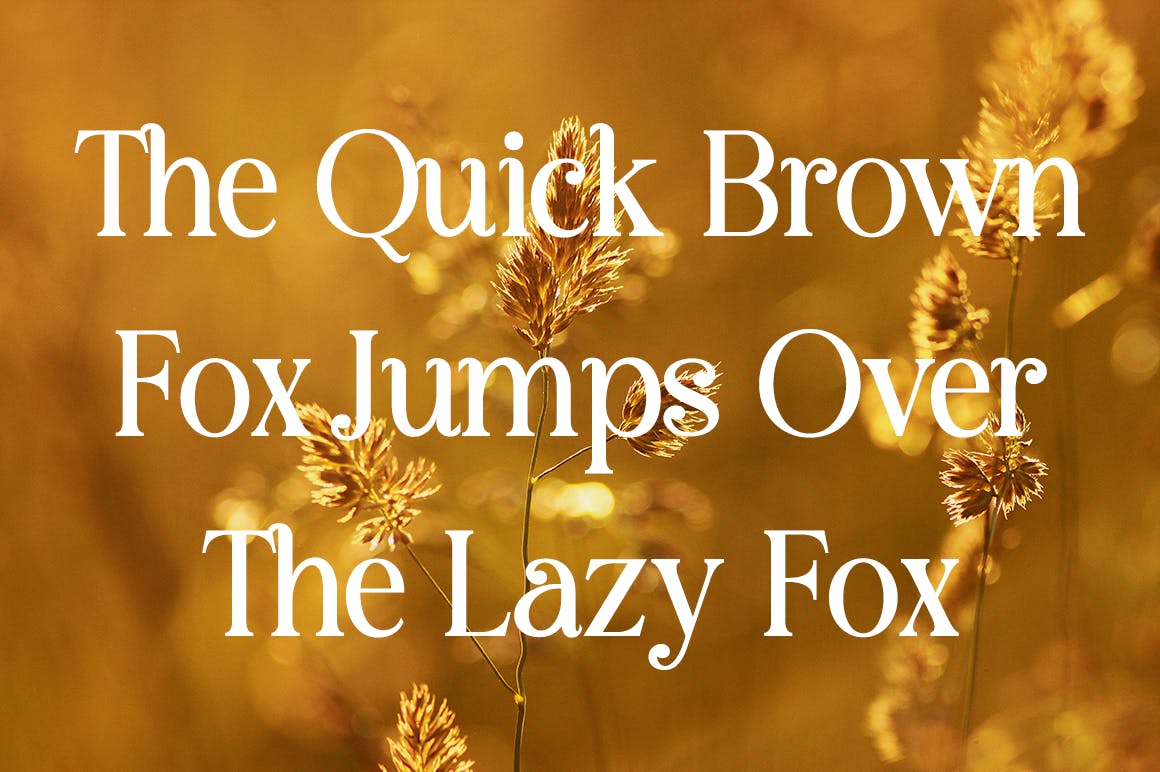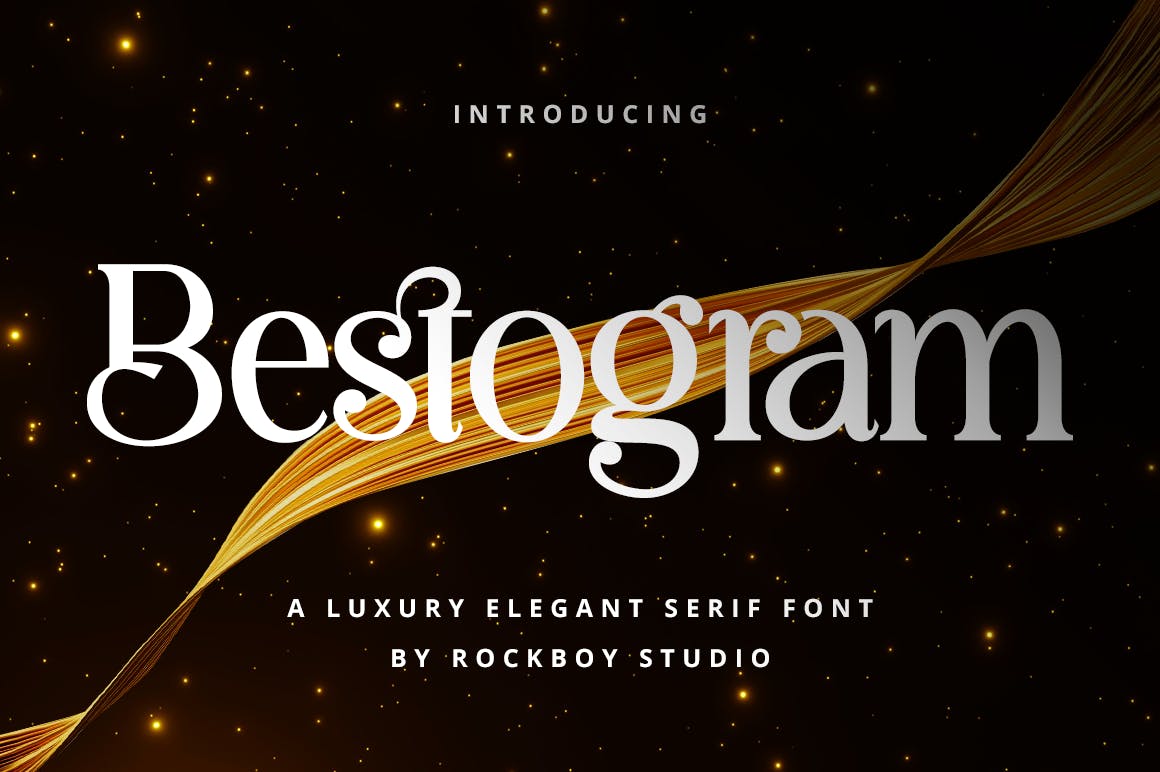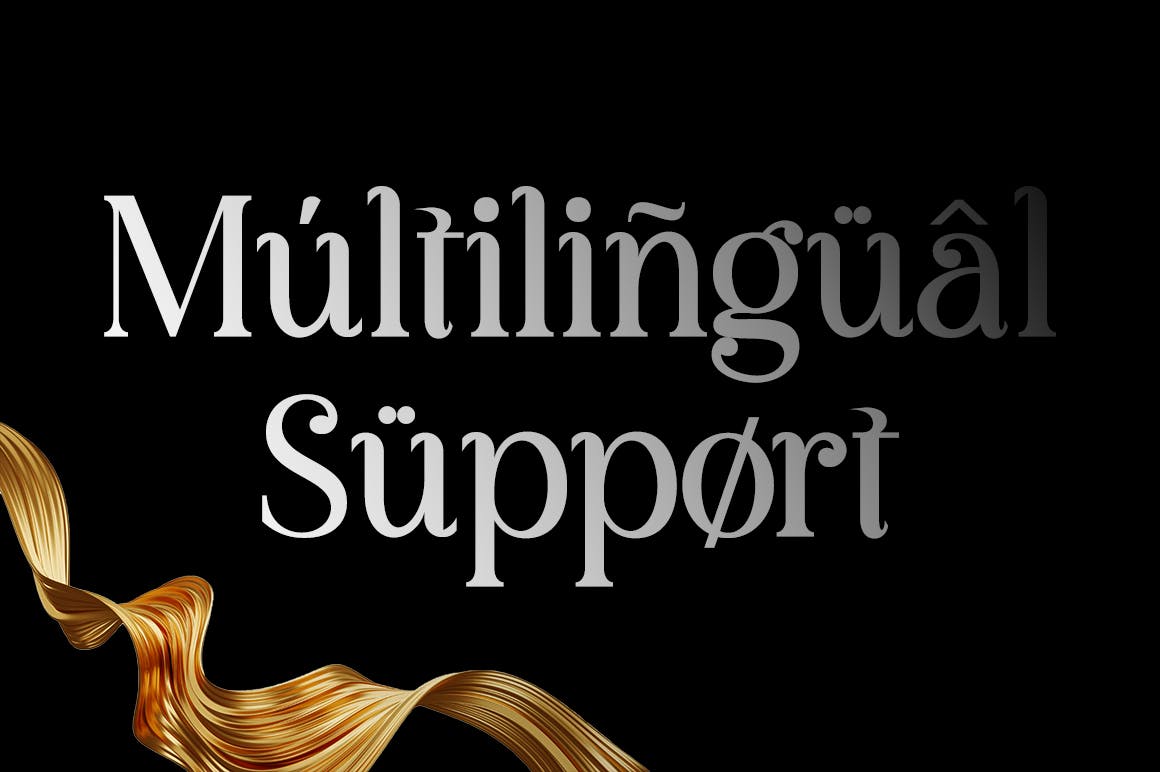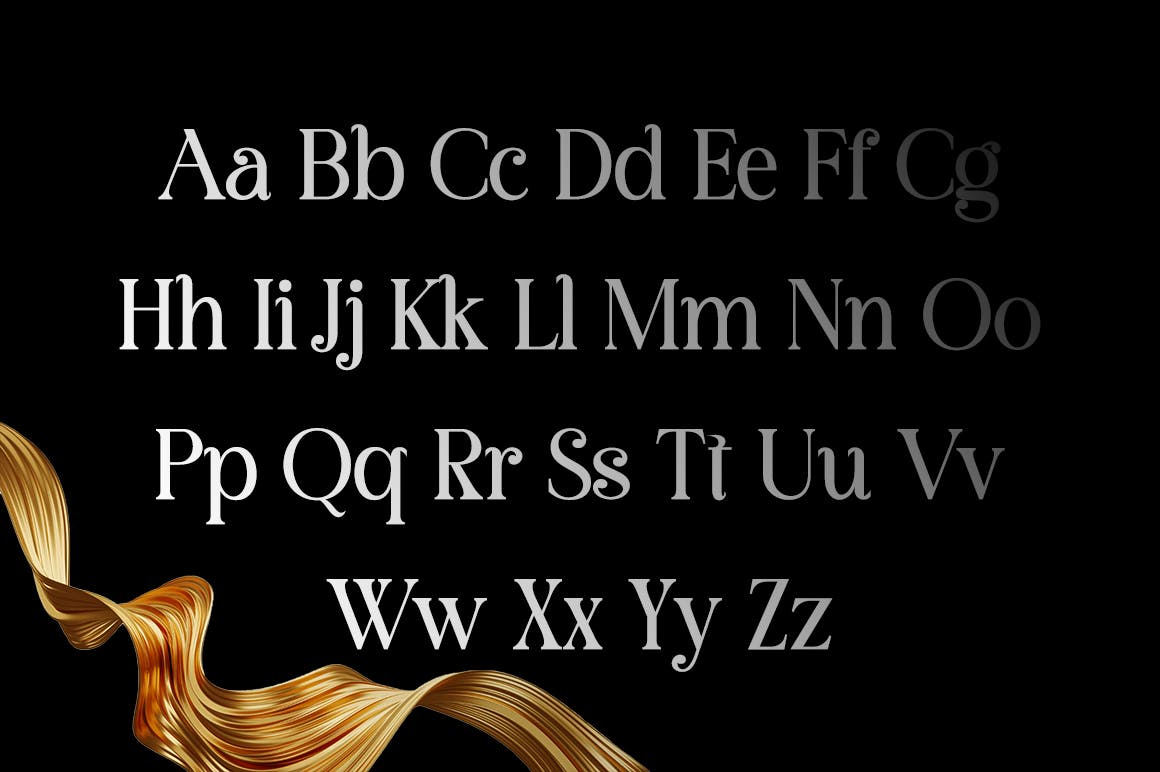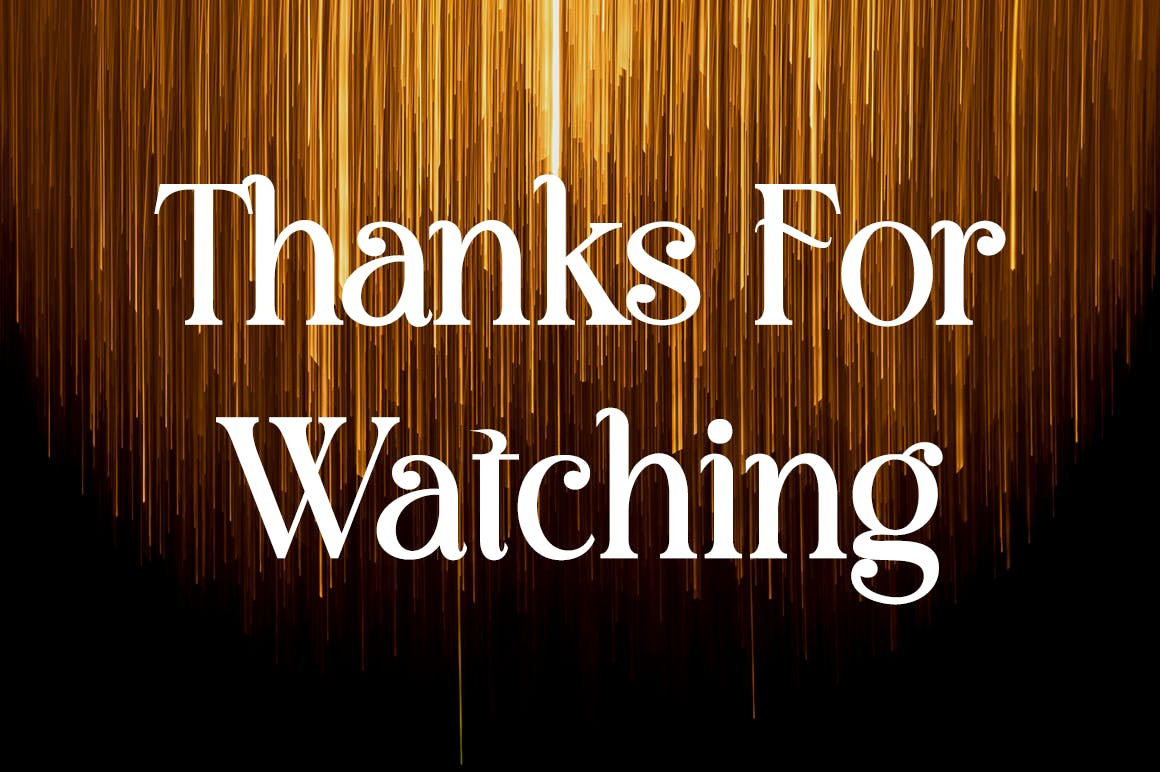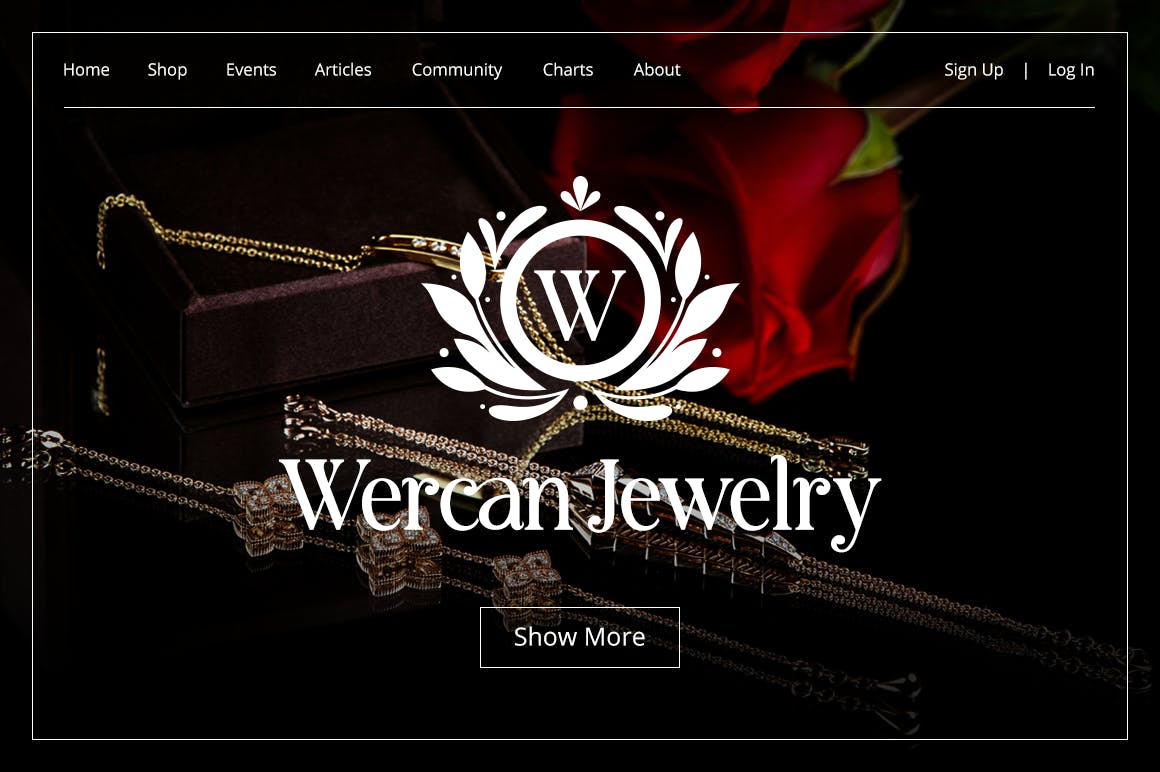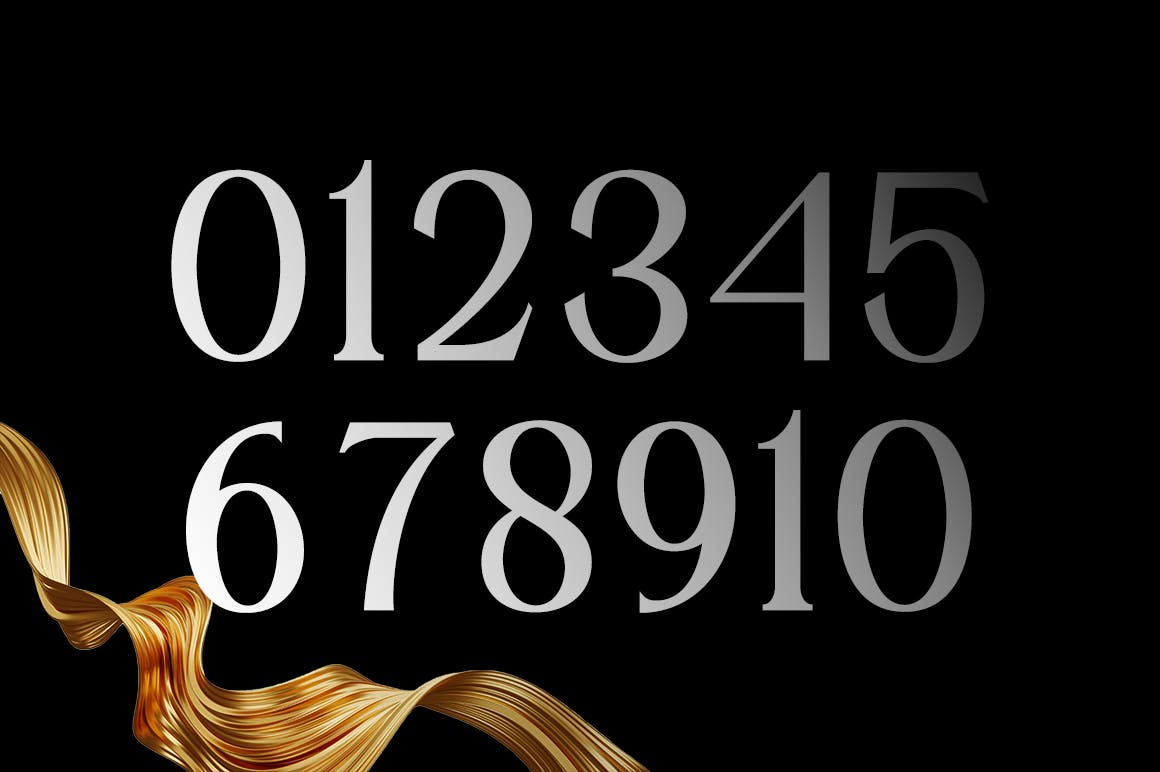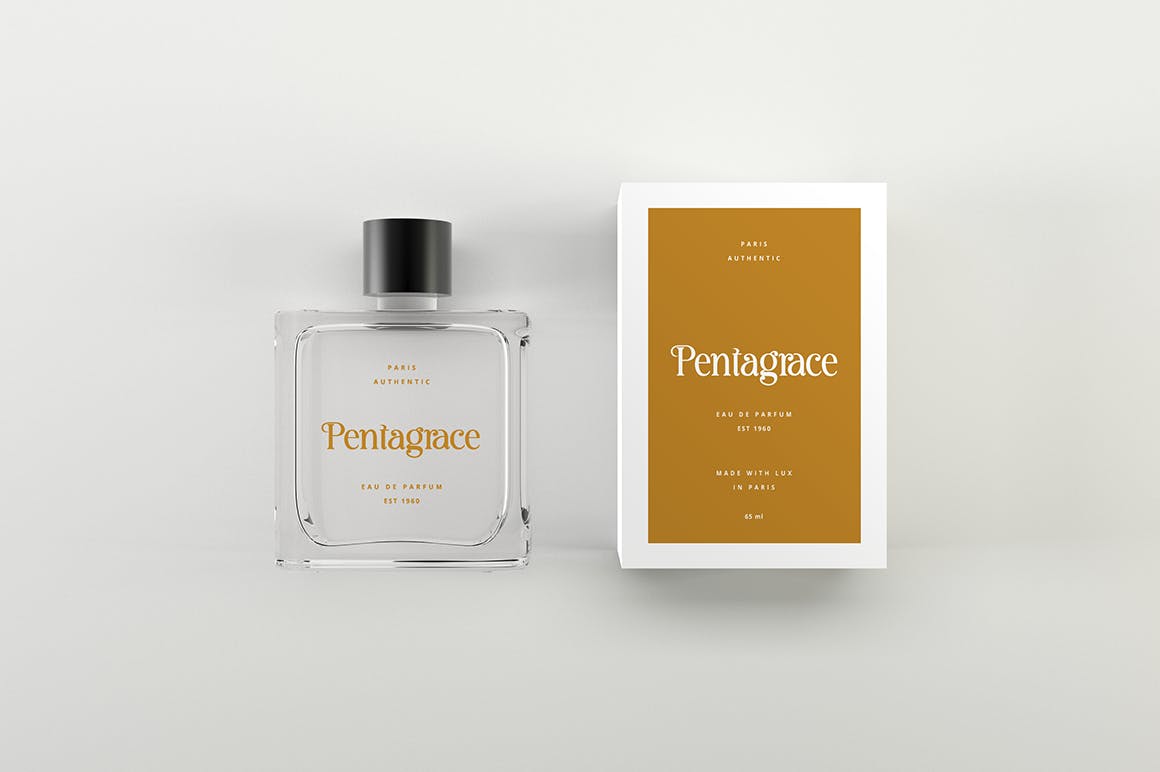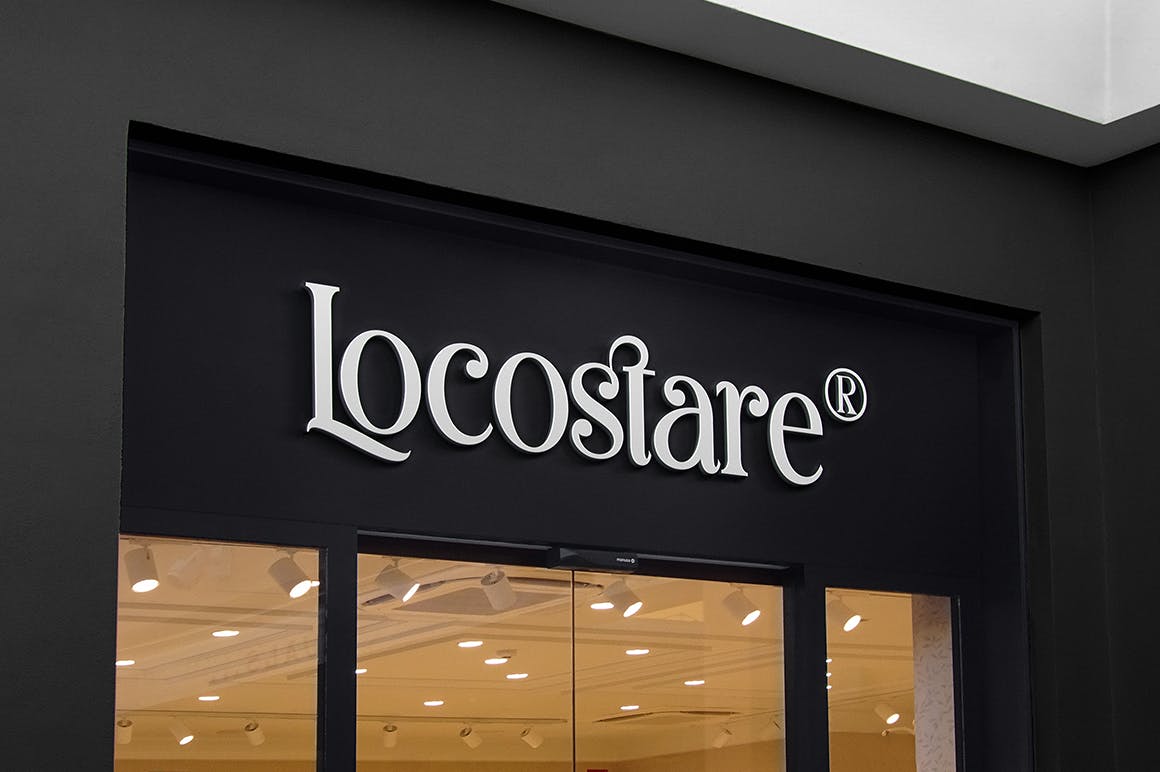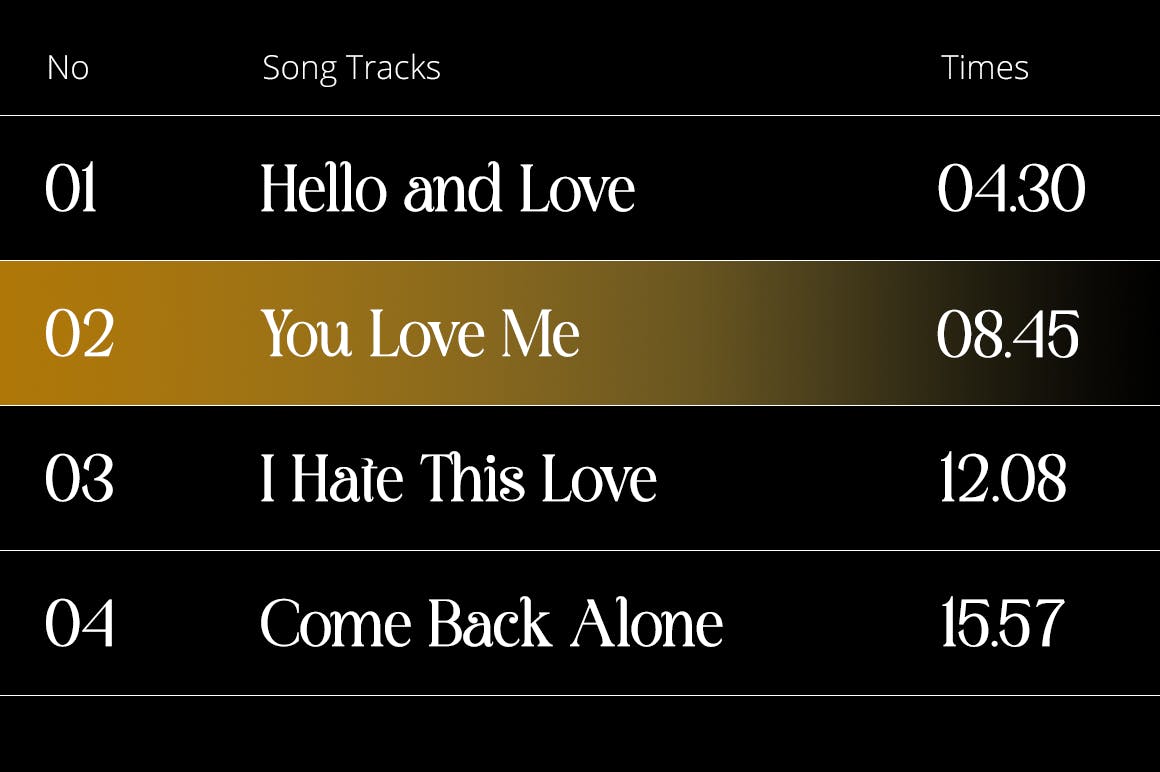
Bestogram یک فونت سریف شیک و منحصر به فرد است. این فونت به دلیل سبک مرتب و سادهاش، مناسب برای طراحیهای متنوعی است و میتواند به فونت مورد علاقه شما تبدیل شود، بیتوجه به مناسبت!